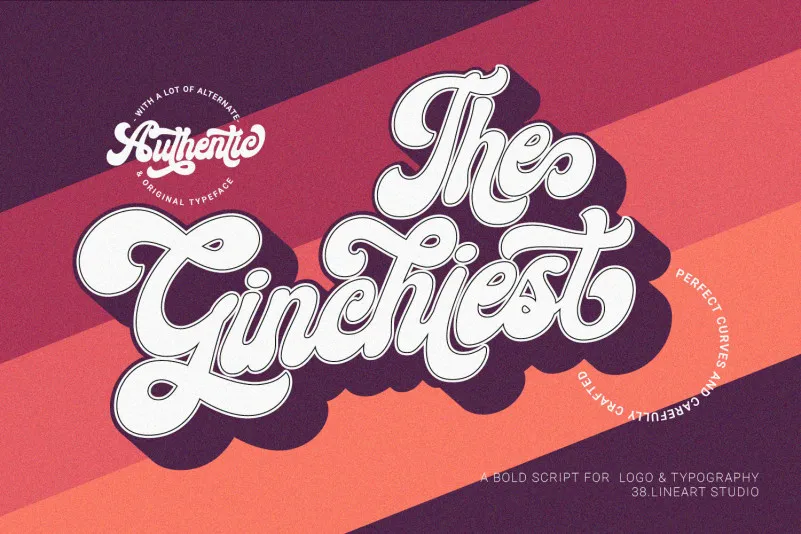
Ginchiest Font – Download Grátis
A Ginchiest Font é uma fonte de letra cursiva que carrega um estilo vintage retro, perfeita para amantes do lettering. Esta font oferece alternativas e ligaturas extremamente atraentes, tornando-a um recurso visual irresistível. A 38.lineart criou esta font com grande cuidado, incluindo detalhes que garantem tanto a elegância quanto a originalidade da sua escrita artesanal. Se você é fã de letraing e busca expressar seu design através do texto, a Ginchiest Font é uma escolha perfeita para personalizar seus trabalhos de arte, desde pequenos cartões até grandes projetos gráficos.